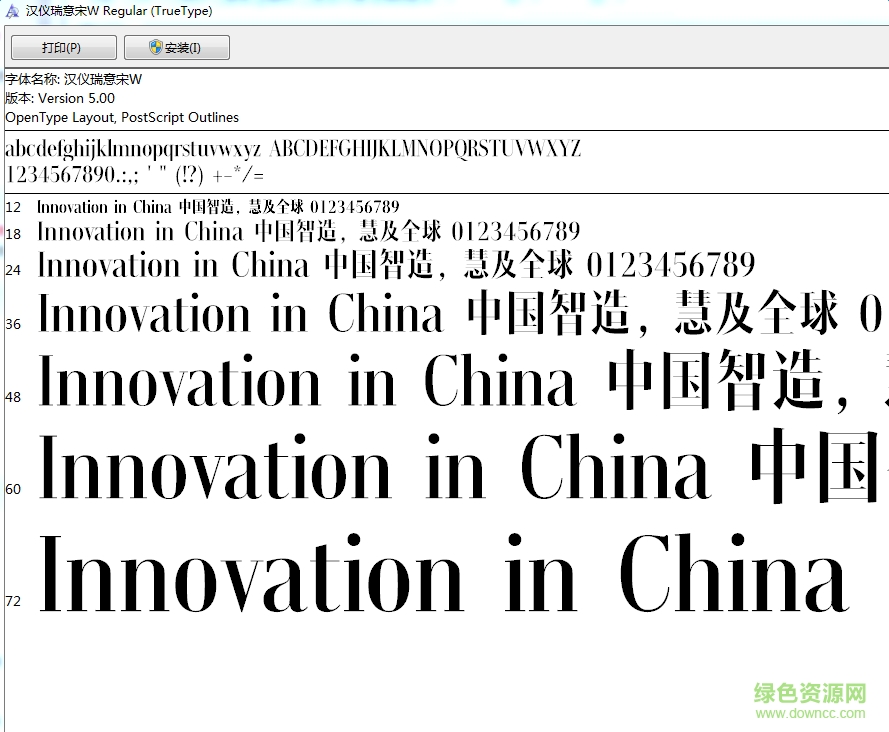
漢儀瑞意宋字體是一款漢儀類文雅宋體風(fēng)格字體軟件,瑞意宋體筆畫工整,棱角突出,完美闡釋了宋體文雅特色,深受廣大書法家喜愛,還有更多好看字體歡迎來綠色資源網(wǎng)下載體驗!
漢儀瑞意宋字體是一款應(yīng)用于藝術(shù)設(shè)計方面的簡體中文字體,該字體筆畫粗壯,尾部的甩尾有力且有豐富的筆觸細(xì)節(jié),大字效果突出且引人注目;并且最大程度還原作者書寫字形,細(xì)節(jié)表現(xiàn)完整,且字庫完整,可以廣泛應(yīng)用于名片設(shè)計、新聞媒體、宣傳海報、ppt、影視制作以及內(nèi)容用字等領(lǐng)域。